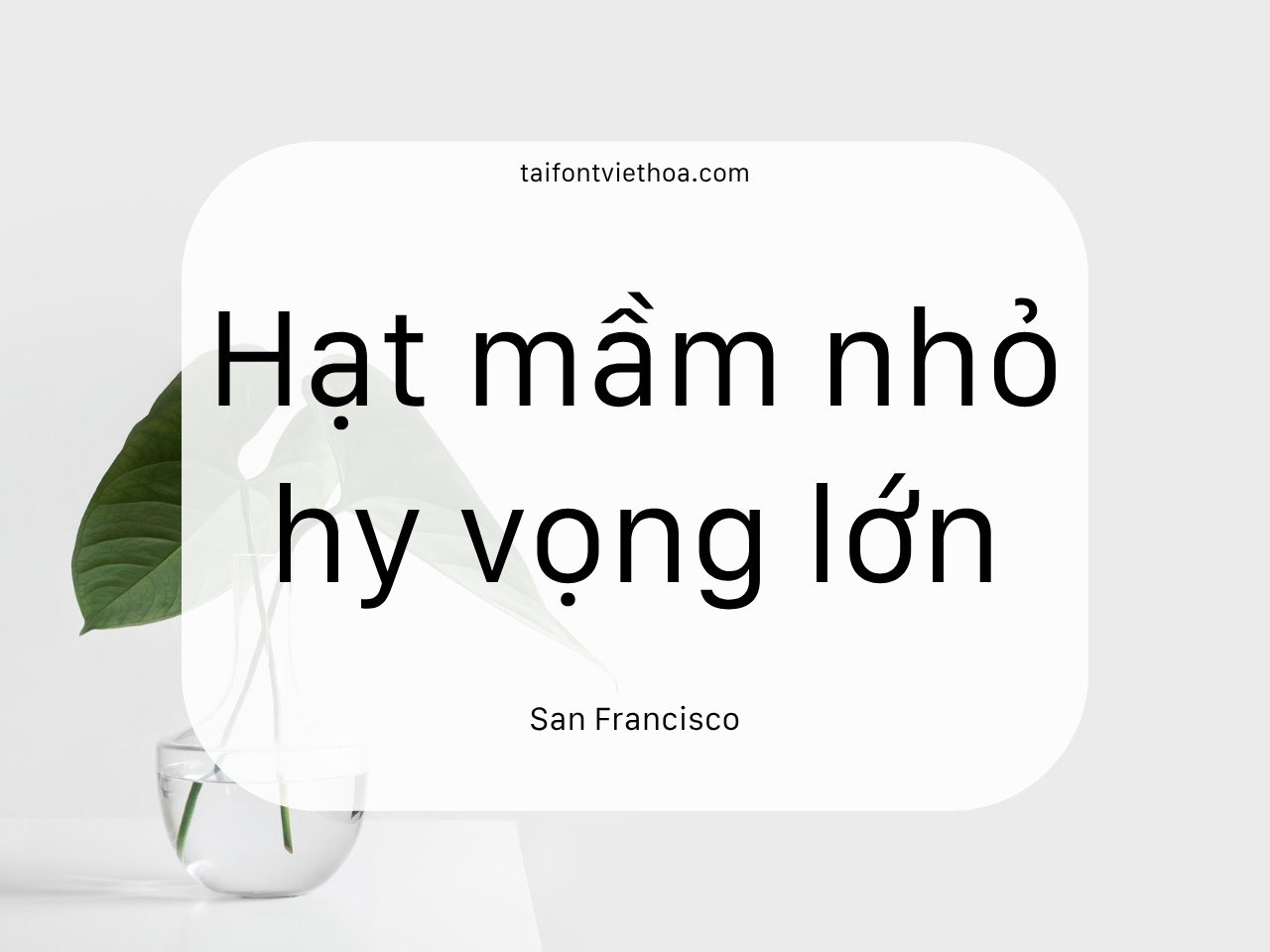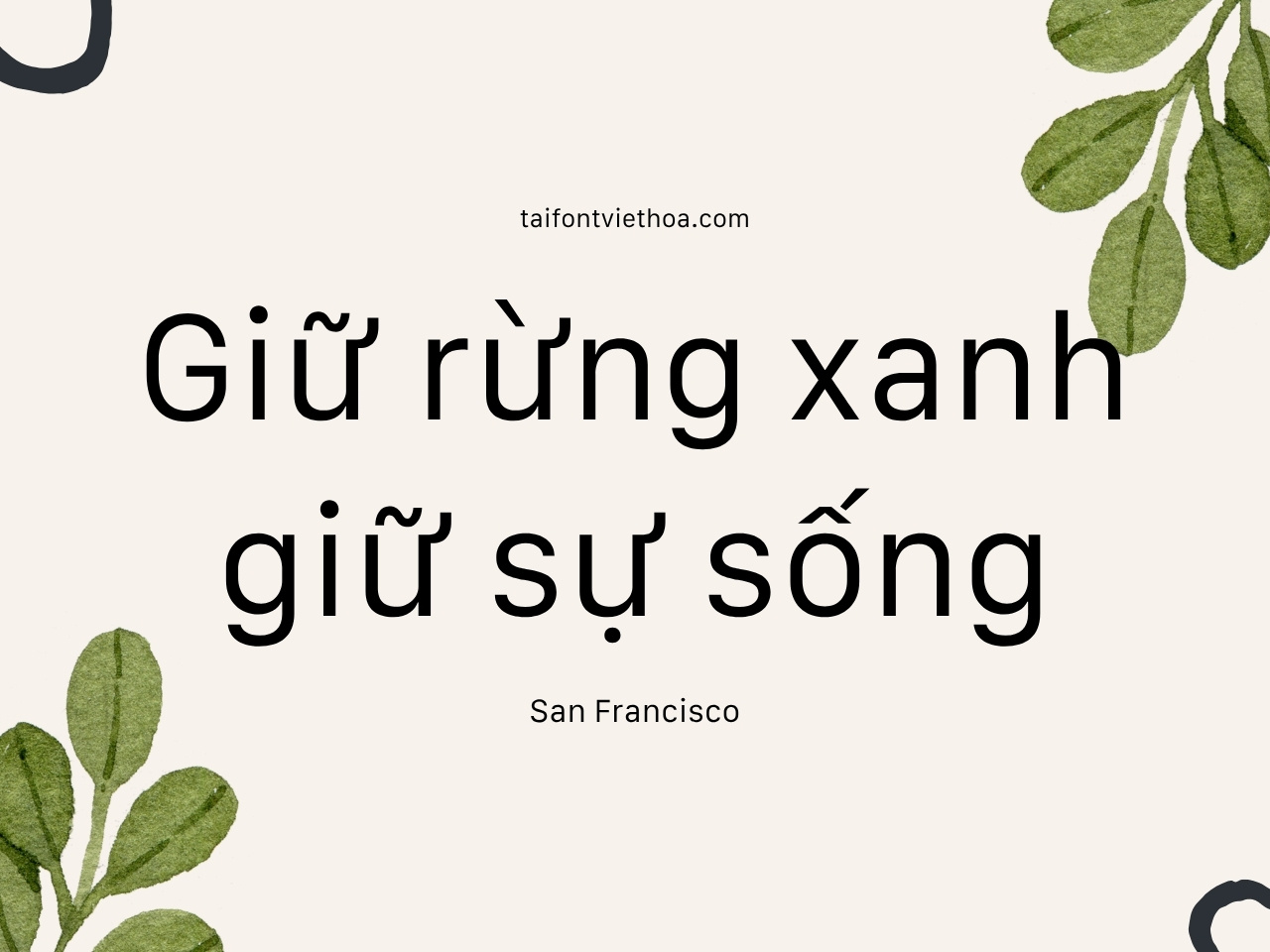
Font việt hóa San Francisco đầy đủ
Giới thiệu về font San Francisco
San Francisco là bộ font sans-serif hiện đại được Apple phát triển nội bộ từ năm 2015 nhằm thay thế Helvetica Neue làm font mặc định trên các hệ điều hành như macOS, iOS, iPadOS và watchOS. Font được thiết kế tối ưu cho cả khả năng đọc trên màn hình lẫn hiển thị in ấn với độ chính xác cao. Hiện tại, San Francisco có nhiều biến thể như SF Pro, SF Compact, SF Mono… và hỗ trợ hơn 150 ngôn ngữ dùng hệ ký tự Latinh, Cyrillic và Greek.
Phiên bản Việt hóa trọn bộ được cộng đồng thiết kế cập nhật để phù hợp với hệ thống Unicode tiếng Việt, giữ nguyên cấu trúc và sự tối ưu ban đầu của Apple. Font này đã được taifontviethoa.com sưu tầm, kiểm tra và giới thiệu lại cho cộng đồng người dùng Việt Nam nhằm phục vụ các dự án UI/UX, thiết kế kỹ thuật số, giao diện hệ điều hành và các ứng dụng đòi hỏi sự chính xác, đồng bộ.
Giới thiệu về font San Francisco
Đặc điểm thiết kế và ứng dụng thực tế
San Francisco sở hữu thiết kế sans-serif gọn gàng, chữ cái cân đối, khoảng cách chữ tối ưu và độ tương phản thấp giúp dễ đọc trên cả màn hình nhỏ lẫn in ấn khổ lớn. Font được chia thành các phiên bản có cấu trúc khác nhau như Pro Display (cho tiêu đề), Pro Text (cho nội dung dài), và SF Mono (cho mã lập trình), tạo nên hệ thống chữ toàn diện và dễ ứng dụng.
Font này lý tưởng trong các lĩnh vực công nghệ, bất động sản, giáo dục kỹ thuật số, truyền thông UI/UX, hoặc các hệ thống phần mềm. Ngoài ra, San Francisco cũng là font mặc định cho giao diện Apple Watch và hệ sinh thái iPhone, MacBook nên rất thích hợp với các sản phẩm thương hiệu cao cấp, trình bày dashboard, app mobile, thiết kế sản phẩm công nghệ và hệ thống quản trị.